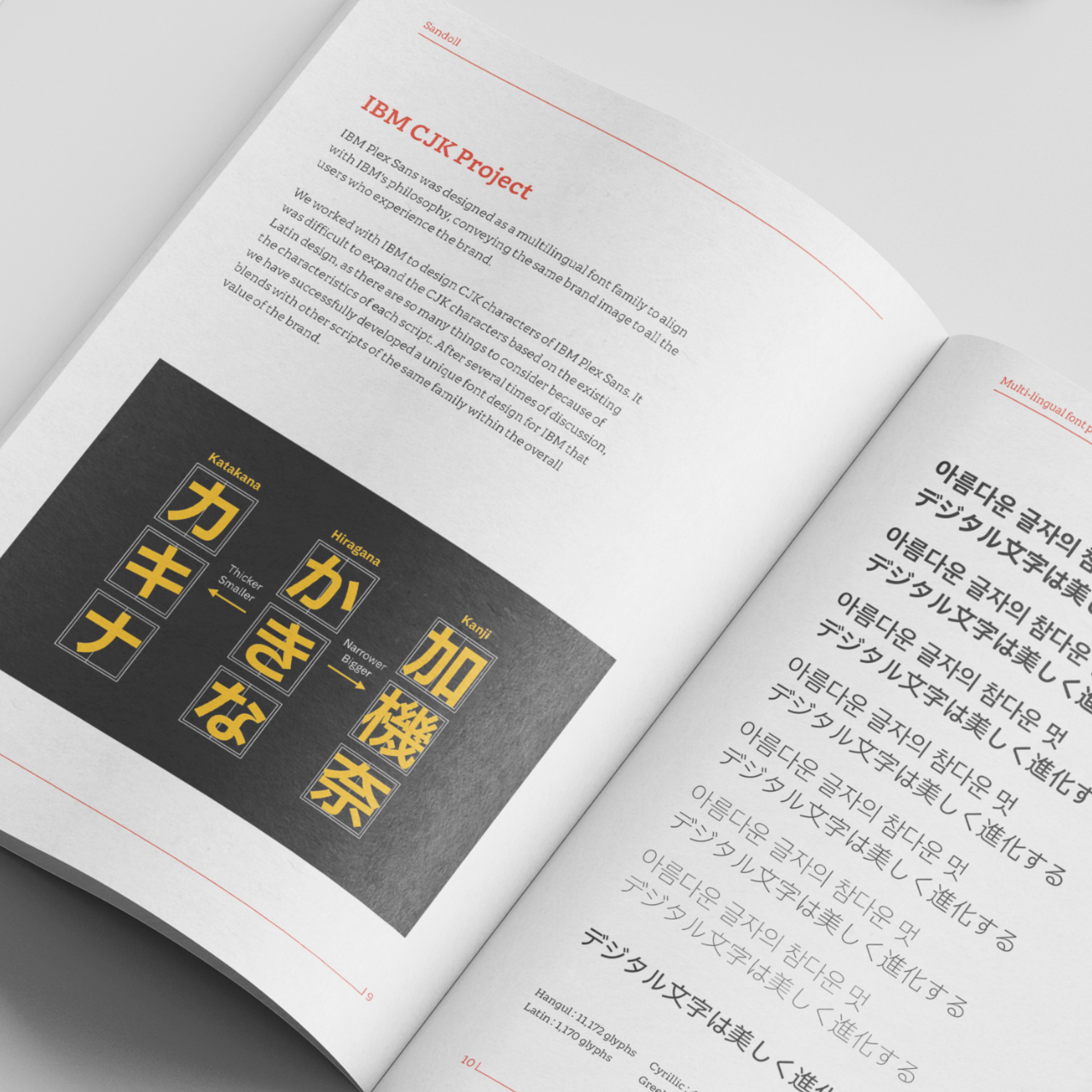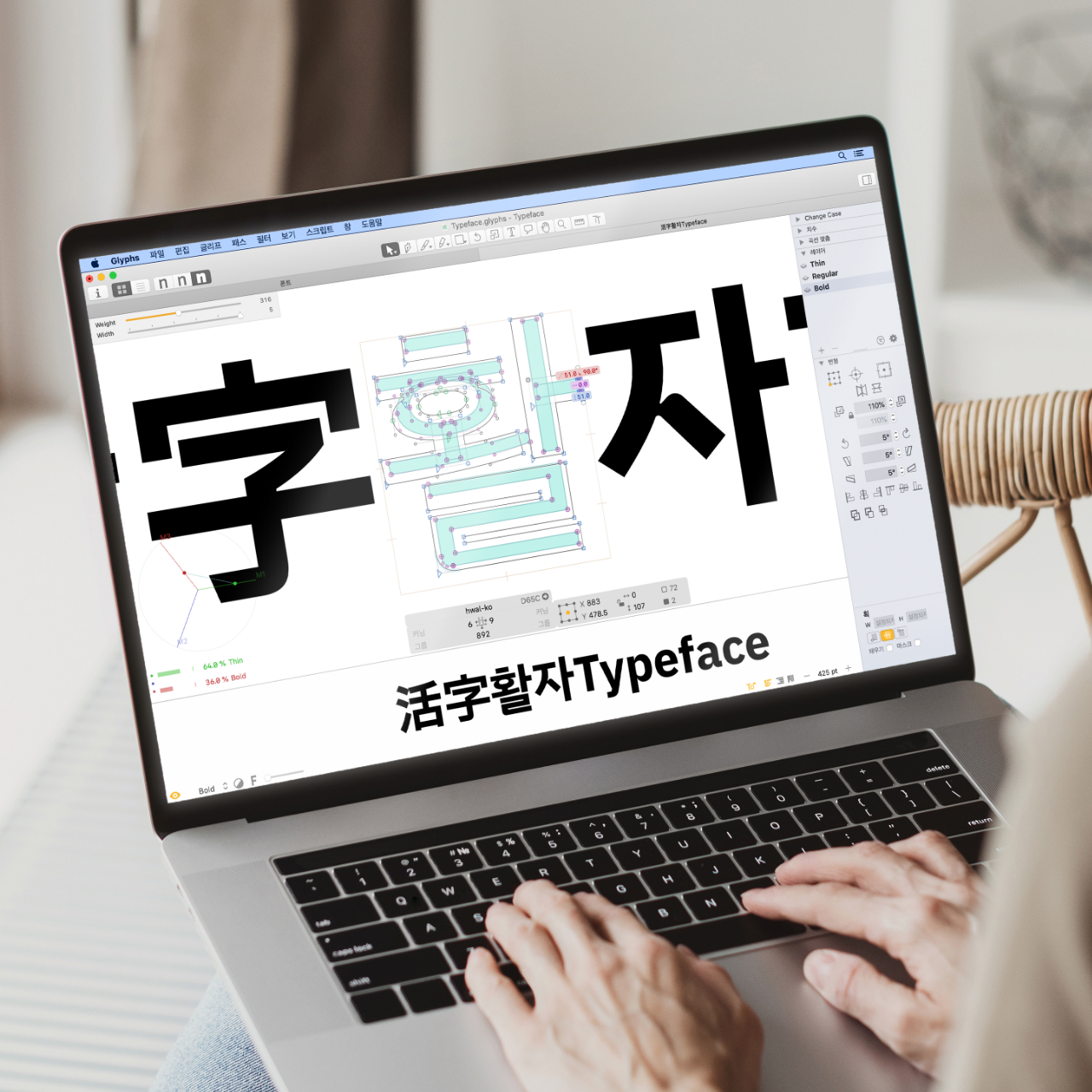
타입브랜딩은 고유한
목소리를 만듭니다
글자의 모양새에는 소릿값이 담겨있습니다. 나긋나긋하고 쫑알쫑알하며 쩌렁쩌렁 속삭이고 외칩니다. 산돌은 브랜드의 목소리를 함께 상상하고 만들어 갑니다. 자신에게 꼭 맞는 목소리를 찾은 브랜드는 텍스트를 이야기로 바꿉니다. 같은 말도 어떻게 말하는가에 따라 다르듯, 일상 속 다양한 커뮤니케이션 경험은 브랜드 전용폰트의 이유입니다. 산돌은 고유한 목소리로 이야기하는 브랜드를 경험할 때마다 지속가능한 오리지널리티의 가능성을 확신합니다.
글로벌 폰트는 하나의 목소리로 다국어를 말합니다
산돌은 1984년 올곧은 한글 디자인을 꿈꾸며 시작하였고 지금은 라틴에서 한자, 가나에 이르기까지 지구의 절반 이상을 덮는 글로벌 폰트를 스스로 만듭니다. 유럽과 아메리카, 동아시아의 중국어, 일본어가 하나의 폰트 폰트 패밀리로 어울리기란 쉽지 않습니다. 글로벌 폰트는 여러 폰트 파운드리의 협업하기 때문에 커뮤니케이션이 복잡해지는 문제가 있습니다. 산돌은 오랫동안 손발을 맞춘 오케스트라처럼 견고한 팀을 꾸리고 협주하며 빠르고 정확한 커뮤니케이션으로 글로벌한 목소리를 만듭니다.
디자이너와 엔지니어가 함께 만듭니다
산돌은 디지털폰트의 여명기에 창업하여 디지털 격변기를 겪었고 기업의 전용 폰트에 집중하며 세계적인 타입브랜딩 시장과 문화를 만들어왔습니다. 한국에서 가장 오랫동안 폰트를 만들어 온 만큼 여러 문제를 풀어가는 과정에서 디자이너와 엔지니어의 협업을 지향하게 되었습니다. 그렇게 제작 도구를 개발하고 프로세스를 간소화하니 더욱 열린 자세로 고객사의 피드백을 경청하고 더욱 적극적으로 새로운 제안을 드릴 수 있게 되었습니다.
구체적으로는 윈도우즈 환경에서 작은 글자의 가독성을 향상하는 한글 매뉴얼 힌팅 기술, 디바이스에 폰트를 설치하지 않고 사용한 글자만 서버에서 빠르게 다운로드하는 웹폰트 기술, 굵기와 너비 등 다양한 속성을 사용자가 지정하는 배리어블 폰트, 다양한 색상과 질감을 적용한 컬러 폰트 등이 있습니다.
브랜드에 공감하고
차근차근 함께 만듭니다
브랜드의 성격에 꼭 맞는 폰트를 만들기 위해 체계적인 3단계의 프로세스를 거칩니다. 산돌에서는 그 과정을 3P라고 부릅니다. 폰트에 대해서 잘 모르는 고객사도 알기 쉽게 이해할 수 있도록 돕고, 마일스톤마다 현재 위치와 진행상황을 공유하며 폰트를 제작합니다.
Prototype
산돌과 고객사가 함께 전용폰트 컨셉을 도출합니다. 산돌은 타입브랜딩 트렌드, 테크니컬 리포트 등을 제공하며 고객사가 폰트를 이해할 수 있도록 컨설팅합니다. 고객사는 브랜드와 서비스를 설명하고 누가 어떤 경험을 해야하는지 고민합니다. 여러 차례의 논의, 프로토타입 제안 및 수정을 거치며 최고의 컨셉을 찾아갑니다.
Product
도출된 컨셉을 통해 글자를 제작합니다. 본 과정에서 가장 중요한 것은 현 단계를 명확히 이해하고 정기적으로 미팅을 진행하는 것입니다. 글자 수가 많아질수록 피드백을 반영하는 시간도 늘어남으로, 적절한 체크 포인트를 제안드립니다. 이를 기반으로 피드백을 반영해가며 글자를 만들어나갑니다.
Publish
만들어진 글자를 폰트 파일로 개발합니다. 다양한 환경에서 의도한대로 작동할 수 있도록 자체적인 사용성 QA를 거칩니다. 베타 폰트를 고객사에서도 시뮬레이션하고 피드백을 반영하며, 이렇게 완성된 폰트 파일을 제공합니다.